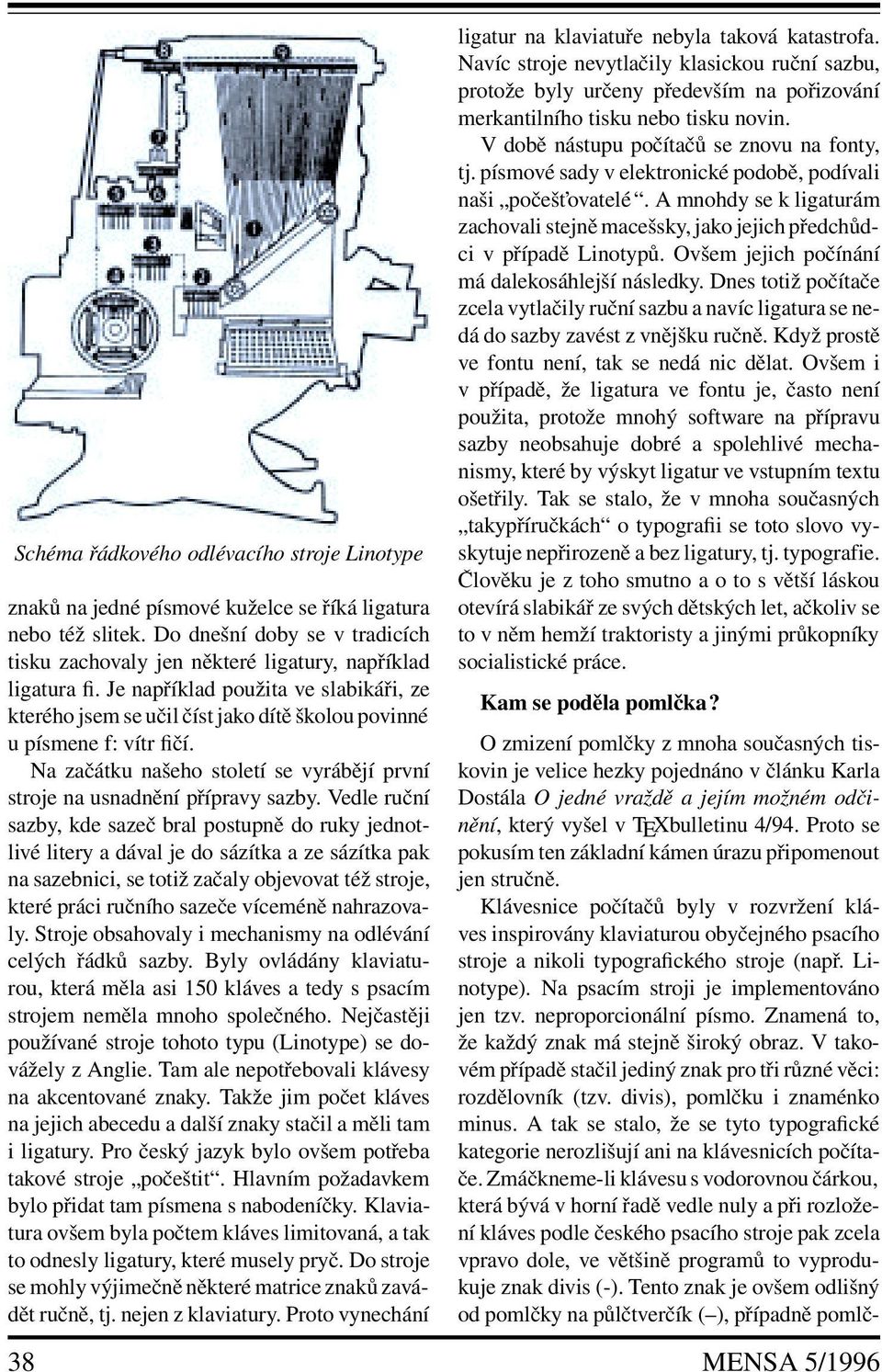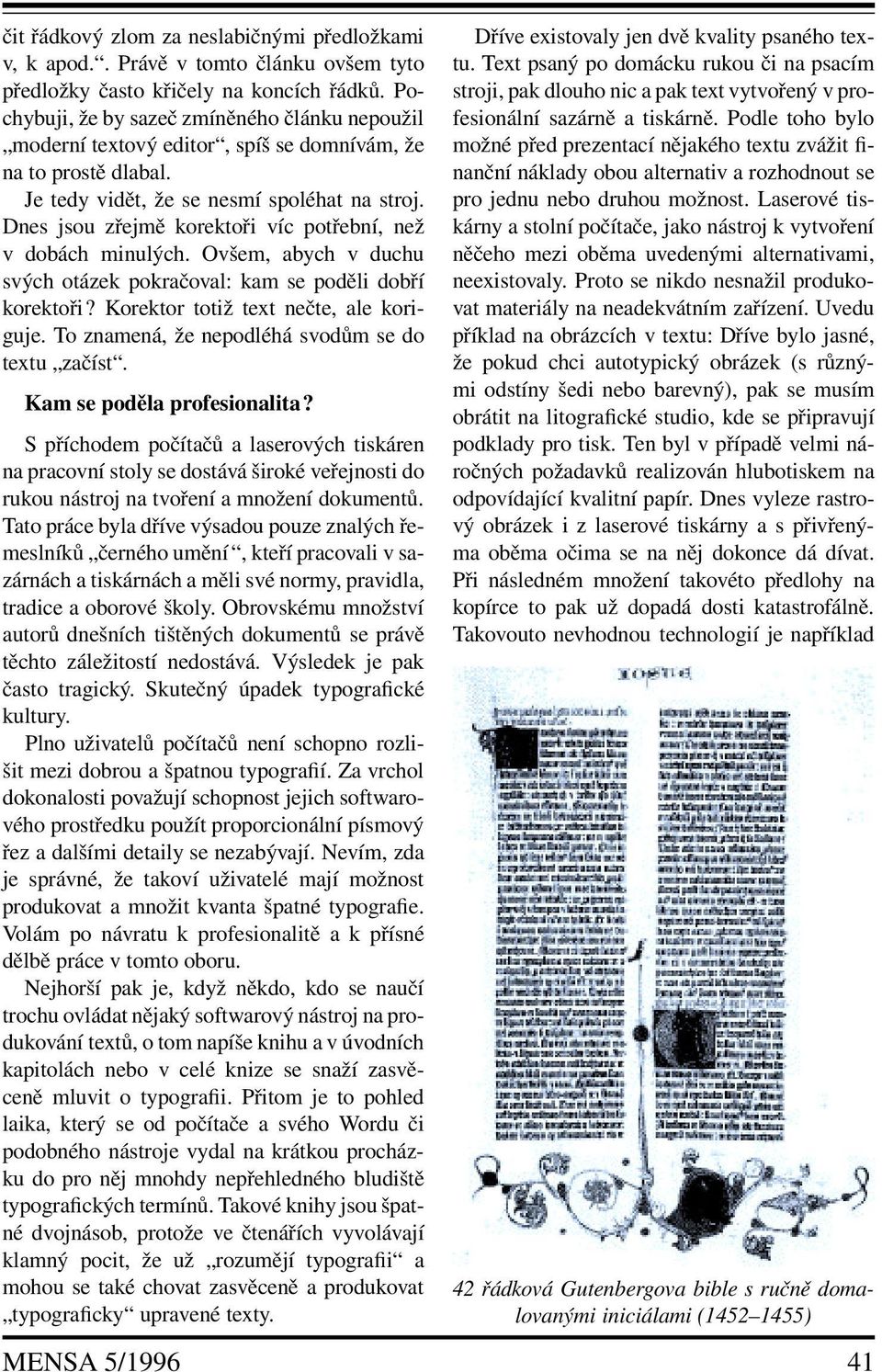
Kam se poděla dobrá typografie?
1 Kam se poděla dobrá typografie? Písmo jako grafické zachycení lidské řeči prošlo v dějinách lidské kultury mnohatisíciletým vývojem. Už pračlověk zřejmě přistoupil ke stěnám své jeskyně s klackem či jiným nástrojem v ruce a začal čmárat grafické značky, kterými vyjadřoval své myšlenky. Dnes jeho prapra-potomek přistupuje k obrazovce počítače, chápe se grafického polohovacího zařízení, zvaného myš, a rovněž čmárá. Bohužel, často toto čmárání nemámyšlenku. V tomto příspěvku nebudu rozebírat dlouholetý vývoj písma, ale zastavím se až v historicky poměrně mladé době, kdy byly objeveny a začaly se používat techniky pro rychlejší rozmnožování textů. Vzniká řemeslo, označované jako černé umění. Staří tiskaři se snažili o co nejvěrnější napodobení vzhledu původních ručně psaných textů. Vytvořili si normy, pravidla a dobré zásady. Vzniká nový obor někde na pomezí mezi technikou pořizování textůavýtvarným uměním typografie. Toto slovo by se dalo volně přeložit jako technologie psaní. V době, kdy Johannes Gensfleisch Gutenberg přišel se svým vynálezem knihtisku (cca 1440), zřejmě plno učenců naříkalo, jaký tento vynález způsobuje obrovský úpadek písma do té doby šířeného pouze ručním přepisováním, jak necitlivě se v tištěných textech projevuje technická rozdílnost pořízení výsledného produktu. Dnes se zpětně na tu dobu díváme s úctou. Nejenže vynález relativně levného rozšiřování písemných dokumentů umožnil prudký rozvoj v rozsáhlém množství vědních oborů, ale také prvotisky, tzv. inkunábule (tisky do r. 1500), jsou dnes považovány za skvosty s vysokou uměleckou hodnotou a muzea si je střeží jako oko v hlavě. Dnes přicházejí na scénu další možnosti v přenosu a sdělování informací. Mám na mysli počítače. Situace se opakuje. Já budu v tomto článku znova upozorňovat na úpadek kultury písma. Samozřejmě, nemohu tušit, co se bude dít za 500 let. Budou se muzea přetahovat o první elektronické inkunábule první CDčka s dokumenty z naší doby? Budou je považovat za umělecké klenoty? A co texty připravené dnes elektronicky v počítačích a vytištěné na papír? Když se podíváme na mnohé strakaté magazíny, které dnes zaplavily stánky s periodiky, musíme zcela rozhodně a nahlas prohlásit, že totoje skutečnému umění na hony vzdáleno. Abychom lépe poznali, jak se nám v dnešní počítačové éře postupně vytrácí zvelkého množství dnes tištěných textů dobrá typografie, vrat me se o pár letzpátky a sledujme jen několik typických fenoménů spojených s problematikou tisku. Ligatury, pomlčky, měrný systém a lidský přístup. Kam se poděly ligatury? Jak již bylo řečeno, první tiskaři se snažili o co nejvěrnější napodobení psaného písma. Neměli proto ve svých písmových sadách jen samostatné znaky, ale rovněž spojení několika znaků v jeden celek, jak to tehdy odpovídalo tradicím ručně psaných textů. Takovému spojení Johannes Gensfleisch Gutenberg ( ) MENSA 5/
2 Schéma řádkového odlévacího stroje Linotype znaků na jedné písmové kuželceseříká ligatura nebo též slitek. Do dnešní doby se v tradicích tisku zachovaly jen některé ligatury, například ligatura fi.je například použita ve slabikáři, ze kterého jsem se učil číst jako dítě školou povinné upísmene f: vítr fičí. Na začátku našeho století se vyrábějí první stroje na usnadnění přípravy sazby. Vedle ruční sazby, kde sazeč bral postupně do ruky jednotlivé litery a dával je do sázítka a ze sázítka pak na sazebnici, se totiž začalyobjevovat též stroje, které práci ručního sazeče víceméně nahrazovaly. Stroje obsahovaly i mechanismy na odlévání celých řádků sazby. Byly ovládány klaviaturou, která měla asi 150 kláves a tedy s psacím strojem neměla mnoho společného. Nejčastěji používané stroje tohoto typu (Linotype) se dovážely z Anglie. Tam ale nepotřebovali klávesy na akcentované znaky.takže jim počet kláves na jejich abecedu a další znakystačil a měli tam i ligatury. Pro český jazyk bylo ovšem potřeba takové stroje počeštit. Hlavním požadavkem bylo přidat tam písmena s nabodeníčky. Klaviatura ovšem byla počtem kláves limitovaná, a tak to odnesly ligatury, které musely pryč. Do stroje se mohly výjimečně některé matrice znaků zavádět ručně, tj. nejenzklaviatury. Protovynechání ligatur na klaviatuře nebyla taková katastrofa. Navíc stroje nevytlačily klasickou ruční sazbu, protože byly určeny především na pořizování merkantilního tisku nebo tisku novin. V době nástupu počítačů se znovu na fonty, tj.písmové sady v elektronické podobě, podívali naši počešt ovatelé. A mnohdy se k ligaturám zachovali stejně macešsky,jakojejichpředchůdci v případě Linotypů. Ovšem jejich počínání má dalekosáhlejší následky. Dnes totiž počítače zcela vytlačily ruční sazbu a navíc ligaturasene- dá dosazbyzavést z vnějšku ručně. Když prostě ve fontu není, tak se nedá nicdělat. Ovšem i vpřípadě, že ligatura ve fontu je, často není použita, protože mnohý softwarenapřípravu sazby neobsahuje dobré a spolehlivé mechanismy, které byvýskyt ligatur ve vstupním textu ošetřily. Tak se stalo, že v mnoha současných takypříručkách o typografii se toto slovo vyskytuje nepřirozeně a bez ligatury, tj. typografie. Člověku je z toho smutno a o to s větší láskou otevírá slabikář zesvých dětských let,ačkoliv se tovněm hemží traktoristy a jinými průkopníky socialistické práce. Kam se poděla pomlčka? O zmizení pomlčky z mnoha současných tiskovin je velice hezky pojednáno v článku Karla Dostála O jedné vraždě a jejím možném odčinění, kterývyšel v TEXbulletinu 4/94. Proto se pokusím ten základní kámen úrazu připomenout jen stručně. Klávesnice počítačů byly v rozvržení kláves inspirovány klaviaturou obyčejného psacího stroje a nikoli typografického stroje (např. Linotype). Na psacím stroji je implementováno jen tzv. neproporcionální písmo. Znamená to, že každý znakmástejně široký obraz. V takovémpřípadě stačil jediný znakprotři různévěci: rozdělovník (tzv. divis), pomlčku i znaménko minus. A tak se stalo, že se tyto typografické kategorie nerozlišují ani na klávesnicích počítače.zmáčkneme-li klávesu s vodorovnou čárkou, která bývá v horní řadě vedle nuly a při rozložení kláves podle českého psacího stroje pak zcela vpravo dole, ve většině programů to vyprodukuje znak divis (-). Tento znak je ovšem odlišný od pomlčky na půlčtverčík ( ), případně pomlč- 38 MENSA 5/1996
3 ky na čtverčík ( ), případně znaménka minus v matematické sazbě ( ). Není pravda, že v počítačových fontech není kromě znaku divis též nějaký typ pomlčky. Faktem zůstává pouze to, že se znak pomlčky v mnoha softwarových produktech musí vyvolat pracně nějakou netriviálníkombinací: například Alt 0151 nebo dlouhým lovením v nabídkách fontů pomocí myši. To samozřejmě plno lidí nedělá. Možná, že mnoho lidí ani neví, že pokud v dřívějších dobách sazeč nerozeznal pomlčku od znaku divis, měl umistra značné problémy a pokud se to opakovalo, pak mohl přijít i vyhazov. Kdyby tomu tak bylo i dnes, pak by sazeči z valné většiny současných deníků byli už dávno vyhozeni z práce. Kde se vzalo tolik ignorance vůči pomlčce? Určitě v tom nemalou roli hraje skutečnost rozdělení práce mezi autorem textu a sazečem. Autor textuvětšinou připravuje své dílovjiném editoru, než sjakým se pracuje při sazbě. Je též běžné, že se autor o pomlčky nestará, protože otom možná nic neví, nebo toani vjeho editoru nelze rozlišovat (T602). Za to samozřejmě autora nesmíme zlořečit ani v dřívějších dobách, kdy dodával do tiskárny rukopis psaný strojem, pomlčky nerozlišoval. Viníkem je sazeč, který dostane text od autora v elektronické podobě a neobtěžuje se projít všechny výskyty znaku vodorovná čárka a u každého individuálně zvážit, co tím měl autor na mysli: zda divis, pomlčku na půlčtverčík, na čtverčík nebo matematické minus. Přitom, jak vidíme, mu za to nehrozí žádný vyhazov z práce. Bohužel. Kam se poděl Didotův měrný systém? Trvalo 300 let od Gutenbergova vynálezu, než se tiskaři v celé kontinentální Evropě sjednotili na jednotce, kterou označovali míry v typografii. Touto jednotkou byl tzv. Didotův bod, který z pohledu dnešní SI soustavy je velký zhruba 0,38 mm. Didotův měrný systém byl odvozen ze soustavy, kde se pracovalo s násobky dvanácti ajakovýchozí byla použita francouzská stopa. Bylo vytvořeno velké množství písmových řezů ve stupních podle tohoto měrného systému. Například písmo ve velikosti 10 bodů se podle Didotovy terminologie nazývá garmond, devítibodové písmo je borgis a osmibodové petit. Je nutno připomenout, že typografové zavedli svůj měrný systém dříve, než fyzikové metry a milimetry. Po zavedení SIužsazeči od svého systému neustoupili. Bylo to nejen kvůli dodržení tradice, ale též z ekonomických důvodů: bylo by potřeba přetavit obrovské množství už existujících písem. Typografové v Anglii se na rozdíl od ostatní Evropy nepodřídili francouzskému diktátu a vytvořili si svůj vlastní bod, odvozený z anglické stopy. Tento bod má velikost asi 0,35 mm a pro Setkání různých technologií MENSA 5/
4 rozlišení jej dále budu nazývat point. Více než sto let si žily anglický a evropský systém vedle sebe bez problémů. První větší zmatení jednotek začalo po dovozu řádkových sázecích strojů z Anglie do kontinentální Evropy. Tyto stroje pracovaly s tzv. setovou jednotkou, která byla stanovena na 1/18 pointu. K druhému zmatení jednotek dochází nyní při importu softwarového vybavení zameriky. VAmericetotižkdysi převzali point. Ovšem Americký palec (inch) není přesně dvanáctina původní anglické stopy a tak vyšel 1 inch na pointů a nikoli na 72. Aby si počítačoví typografové zjednodušili počítání, zavedli tzv. big point, který má velikost přesně 1/72 inch. Tento bod se nejčastěji používá v současném softwarovém vybavení pro sazbu. Podle jednotky big point jsou tedy určovány stupně písma v počítačích, tj. například desetibodové písmo z počítače není totéž co garmond, ale spíš se blíží borgisu. Přesněji 10 big pointů vychází na 9,38 Didotových bodů. Když tedy dnešní typografové používají jména borgis, garmond, petit apod., nikdo pořádně neví, co se tím myslí. Didotův systém se s ná- Bruselská madona, tisk o jednom listu (1418) stupem počítačů sice skoro přestal používat, ale v současných typografických příručkách se často setkáváme s tím, že autor s naprostou vážností klade vedle sebe Didotovu terminologii a big point. To vyvolává úsměv na líci. Ztráta Didotova systému tedy nemá přímý dopad na snížení kvality sazby (na rozdíl od ztráty pomlčky nebo ligatur), ale pouze způsobuje mezi typografickými příručkami komunikační chaos. Kam se poděl lidský přístup? Dříve rozhodoval ruční sazeč nadkaždým řádkovým zlomem individuálně, zatímco dnes tuto únavnou práci řeší algoritmy implementované dosázecích programů.ovšem automatický řádkový zlom vede k mnoha nešvarům. Často vidíme zcela nevhodně rozdělená slova, ale též jinétypografické perly, kterými jsoučtenáři častováni v dnešních periodikách a bohužel někdy i knihách. Mezi nejzábavnější patří rozdělená číslovka, například má tři nuly na dalším řádku. Sazeč z dob ruční sazby by okamžitě místo třech nul na novém řádku napsal slovy tisíc, protože toto mu umožňovaly normy pro ruční sazbu. Takový postup se ovšem strojem zatím nedá nahradit, protože strojnečte při zlomu text jako člověk a tudíž nepřemýšlí nadvýznamem napsané informace. Velmi často jsou čtenáři uráženi rozděleným slovem uprostřed řádku, jako třeba vi- díte zde. To se autor textu pokusil o dělení slov (nebo jeho software se o to pokusil) a sazeč tobezpřemýšlení převzal a před elektronickým zpracováním nezkontroloval. Vúzkých místech se občas vyskytují slova sázená jakoby prokladem. Čtenáře tedy na první pohled napadne, že se jedná ozvýrazněné slovo. Nejedná! To jen sazeč napasíroval text do tak úzkého sloupce, kam by se vůbec neměl dávat. Sázecí program ho neupozornil, že dělá chybu. Místo toho se program snažil vyrovnat okraje za cenu, která se rovná asi nejhoršímu typografickému přestupku: změnil mezipísmennový proklad uvnitř slov. Když něco takového vidím, nejraději bych brečel. Nedávno jsem se v jedněch novinách dočetl, že modernější textové editory umožňují potla- 40 MENSA 5/1996
5 čit řádkový zlom za neslabičnými předložkami v, k apod.. Právě vtomtočlánku ovšem tyto předložky často křičely na koncích řádků. Pochybuji, že by sazeč zmíněného článku nepoužil moderní textovýeditor, spíš se domnívám, že na to prostě dlabal. Je tedy vidět, že se nesmí spoléhat na stroj. Dnes jsou zřejmě korektoři víc potřební, než v dobách minulých. Ovšem, abych v duchu svých otázek pokračoval: kam se poděli dobří korektoři? Korektor totiž textnečte, ale koriguje. To znamená, že nepodléhá svodům se do textu začíst. Kam se poděla profesionalita? Spříchodem počítačů alaserových tiskáren na pracovní stolyse dostává široké veřejnosti do rukou nástroj na tvoření a množení dokumentů. Tato práce byla dříve výsadou pouze znalých řemeslníků černého umění,kteří pracovali v sazárnách a tiskárnách a měli své normy, pravidla, tradice a oborové školy. Obrovskému množství autorů dnešních tištěných dokumentů seprávě těchto záležitostí nedostává. Výsledek je pak často tragický. Skutečný úpadek typografické kultury. Plno uživatelů počítačů neníschopno rozlišit mezi dobrou a špatnou typografií. Za vrchol dokonalosti považují schopnost jejich softwarového prostředku použít proporcionální písmový řez a dalšími detaily se nezabývají. Nevím, zda je správné, že takoví uživatelé majímožnost produkovat a množit kvanta špatné typografie. Volám po návratu k profesionalitě akpřísné dělbě práce v tomto oboru. Nejhorší pak je, když někdo, kdo se naučí trochu ovládat nějaký softwarovýnástroj na produkování textů, o tom napíše knihu a v úvodních kapitolách nebo v celé knize se snaží zasvěceně mluvit o typografii. Přitom je to pohled laika, který se od počítače a svého Wordu či podobného nástroje vydal na krátkou procházku do pro něj mnohdy nepřehledného bludiště typografických termínů. Takové knihy jsou špatné dvojnásob, protože ve čtenářích vyvolávají klamný pocit, že už rozumějí typografii a mohou se také chovat zasvěceně a produkovat typograficky upravené texty. Dříve existovaly jen dvě kvality psaného textu. Text psaný po domácku rukou či na psacím stroji, pak dlouho nic a pak text vytvořený v profesionální sazárně a tiskárně. Podle toho bylo možné před prezentací nějakého textu zvážit finanční náklady obou alternativ a rozhodnout se pro jednu nebo druhou možnost. Laserové tiskárny a stolní počítače, jako nástroj k vytvoření něčeho mezi oběma uvedenými alternativami, neexistovaly. Proto se nikdo nesnažil produkovat materiály na neadekvátním zařízení. Uvedu příklad na obrázcích v textu: Dříve bylo jasné, že pokud chci autotypický obrázek (s různými odstíny šedi nebo barevný), pak se musím obrátit na litografické studio, kde se připravují podklady pro tisk. Ten byl v případě velmináročných požadavků realizován hlubotiskem na odpovídající kvalitní papír. Dnes vyleze rastrový obrázek i z laserové tiskárny a s přivřenýma oběma očima se na něj dokonce dá dívat. Při následném množení takovéto předlohy na kopírce to pak už dopadá dosti katastrofálně. Takovouto nevhodnou technologií je například 42 řádková Gutenbergova bible s ručně domalovanými iniciálami ( ) MENSA 5/
6 připravován časopis společnosti Mensa. Ty obrázky jsou skutečně příšerné. Zpracování textu vtomtočasopisu raději nebudu komentovat. Očasopisu Ericova Alej platí v souvislosti s obrázky víceméně totéž. V tomto případě bych to ale redakci časopisu poněkud více toleroval, protože časopis je určen především pro šíření elektronickou cestou. Početvýtisků napa- píře tedy není přesně určen. Zájemce si časopis vytiskne na takovém zařízení, jaké mák dispozici. Tím zařízením bude asi nejčastěji laserová tiskárna.ve většině papírových kopií bude tedy kvalita obrázků pokulhávat za zpracováním grafiky v časopisech, které jsousvíceny na film a tištěny na kvalitní leštěný papír. Na rozdíl od těchto časopisů jeovšem text v časopise Ericova Alej zpracován po typografické stránce velmi dobře. Ovšem řez písma bych asi volil jiný. Anglickástatická (klasicistická) antikva, zde písmo Computer Modern Donalda Knutha, se asi spíše hodí do odborných publikací a navíc, aby vynikla jeho krása, písmo vyžaduje kvalitní tiskové zpracování. Zde bych volil trochu měkčí řez, třeba některou přechodovou antikvu. Kam se poděli odborníci? V historii české typografie máme mnoho jmen, která svým věhlasem přesáhla hranice naší republiky. Pro ilustraci uvedu jen některá: Vojtěch Preissig, Oldřich Menhart, Josef Týfa, Karel Dyrynk nebo Oldřich Hlavsa. Právě tito lidé povýšili typografii na umění s velmi cennými výtvarnými hodnotami. Kam se poděli žáci a následovníci těchto mistrů? Vidíme, že typografie není jen rutinní práce ručního sazeče, který dodržuje jistá pravidla sazby, ani dnes elektronického programu na sazbu textů,ale též součást výtvarného umění. Dnešní typografičtí umělci, kteří se zabývají návrhem variant písmových řezů, obálek a grafickou úpravou bibliofilií, by měli blíže spolupracovat s dělníky sazeči, kteří sedízasvými QuarkXPressy a dělají jednu chybu za druhou. Zdá semi,že se odborníci zvýtvarné typografie stáhlipřed počítači někam hluboko do pozadí. Také dnešní příručky o typografii jsou vesměs od autorů, kteří se od počítače dostali nějakou náhodou k typografii. Přitom na našem trhu zcela chybí knížka od typografa, který senějakou náhodou dostal k počítačům. Závěrem Tento článek neměl v úmyslu poskytnout návod, jak se chovat, abychom nedělali typografické zmetky. Takový návod totiž neexistuje. Výše uvedené příklady byly jen zrnkem problémů, které se v souvislosti s oborem vyskytují. I v dnešní době existuje plno knih velmi dobře typograficky upravených. Za všechny uved me třeba obnovené vydání titulutypograf o knihách od Karla Dyrynka graficky upravený Martinem Dyrynkem, nebo všem asi dobře známá čtyřdílná monografie Toulky českou minulostí pana Petra Hořejše. Bohužel, v dnešní záplavě počítačem zpracovaných takytiskovin se ty dobré věci stále více ztrácejí. K tomu, aby člověk byl dobrý typograf, nebo aspoň sazeč, rozhodně nestačí přečíst pár typografických příručekodamiči Word odborníků. Je třeba věnovat hodně času studiu typografických tradic, otevřít plno starších bibliofilií, zamyslet se nad grafickou úpravou těchto knížek, často zajít do antikvariátů a hledat ve starších knížkách, všímat si všeho tištěného a přemýšlet o tom z pohledu grafické úpravy a sazby, nechat se inspirovat vším dobrým auvědomovat si jevy špatné, vzít do ruky kaligrafické pero a zkusit něco napsat, ponechat pracovat svůj výtvarný cit ::: Po celou dobu bylo písmo součástí lidské kultury a bylo jí ovlivňováno. Po vynálezu tiskových technik, pomocí nichžsepísmo dostalo do rukou široké skupiny lidí, platí daleko víc než kdy předtím i opačný směr ovlivňování. Písmo působí na lidskou kulturu, stejně jakoarchitektura nebo výtvarné umění. Oslovuje totiž vesměs každého člověka, přičemž lidé způsob prezentace textu nevědomky přijímají. Masové nasazení tiskovýchtechnikprostřednictvím počítačů tentosměr působení jen zesiluje. Proto úpadek písma a typografie vede vlastně kúpadku lidské kultury jako celku. Až zase zasedneme ke svým počítačům súmyslem něco vytisknout, prosím, začněme u toho trochu přemýšlet. PETR OLŠÁK 42 MENSA 5/1996